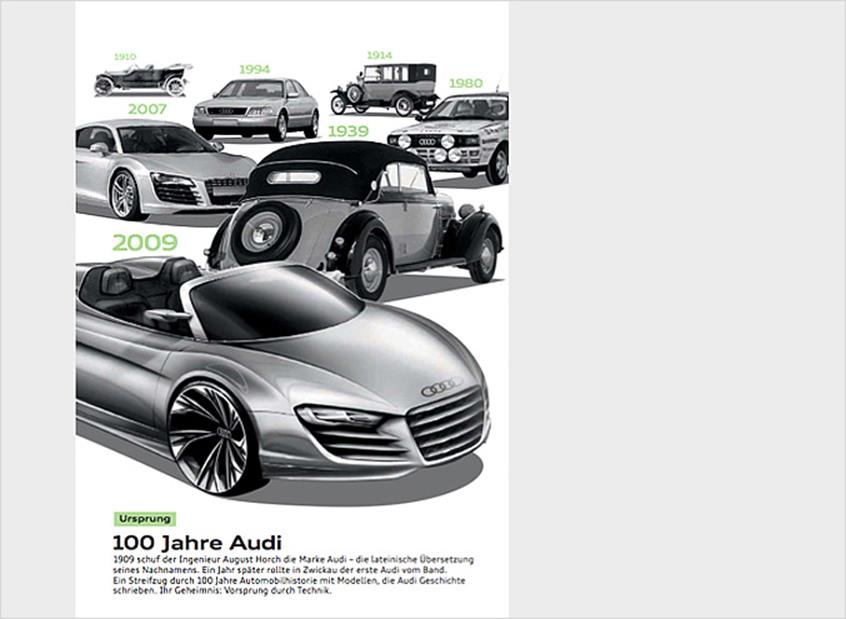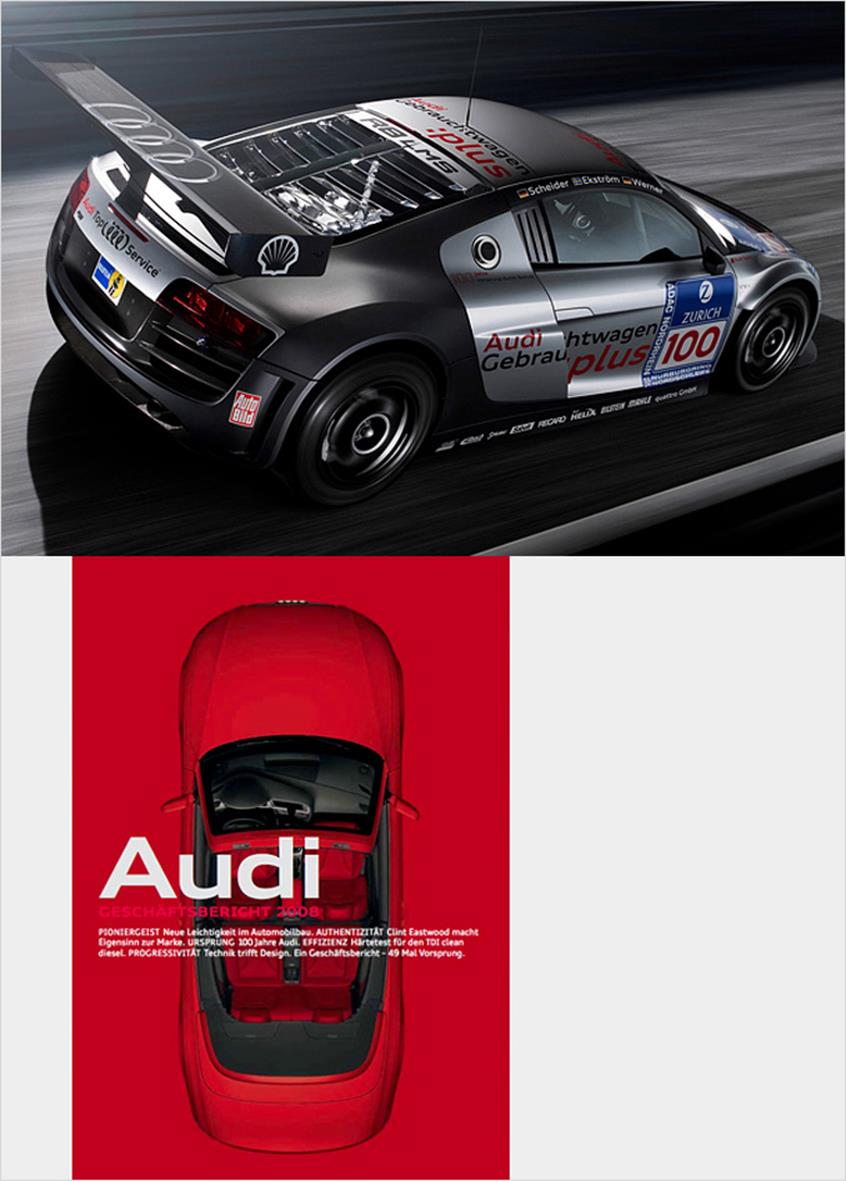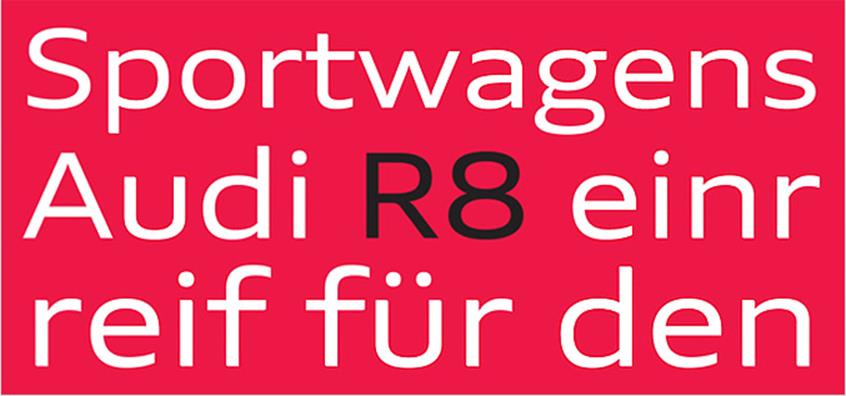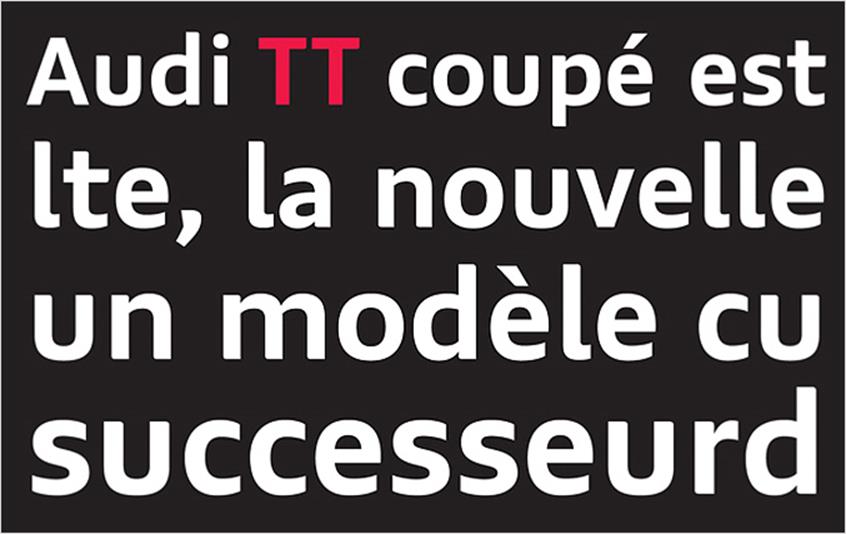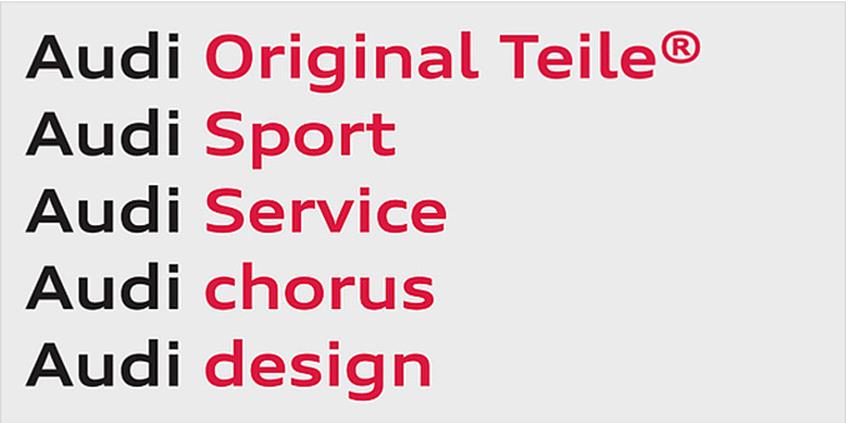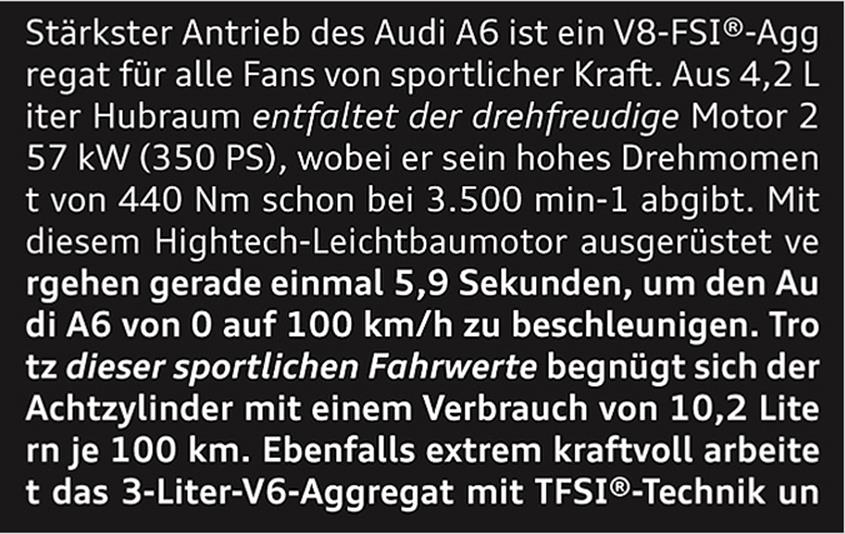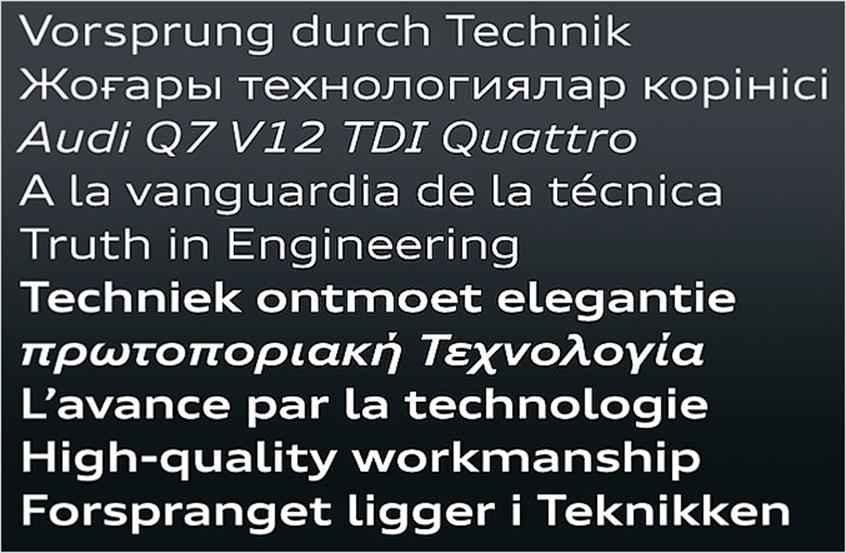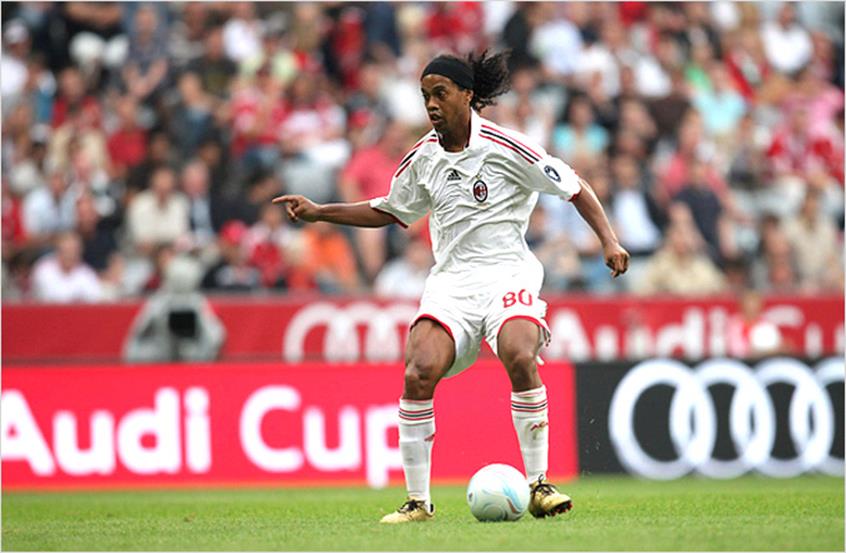
AudiType, Part1_아우디 전용서체의 탄생
2008년 ~ 2009년 사이에 제작된 아우디 전용서체(AudiType)는 출시와 더불어 글로벌 타이포그래피 커뮤니티에 빠르게 전파되어졌다. 이 글에서는 이미 몇 번은 소개되었을 아우디 전용서체의 주요특징 뿐 아니라 메타디자인의 지휘하에 이루어진 디자인 프로세스와 글로벌 브랜드 작업에 포커스를 맞추어 아우티서체를 소개할 것이다. 메타디자인은 아우디 전용서체의 제작을 맡은 베를린의 종합디자인회사이다.
아우디는 이미 잘 알려진 대로 자동차 업계에서 혁신적인 기업으로 꾸준하게 자리매김해온 회사로 고전적 우아함과 기술적 혁신성이 잘 조화된 제품군을 갖추고 있는 독일을 대표하는 브랜드이기도 하다. 독일 잉골슈타트(Ingolstadt)에 자리한 아우디 본사는 설립 100주년을 기념하여 회사 이미지 재고를 위한 여러 프로젝트를 진행시켰고, 그 중 한가지가 기업전용서체의 제작이었다. 디자인 종합회사 메타디자인의 총괄 아래, 아우디 서체의 디자인을 맡게 된 볼드 먼데이(Bold Monday)의 네덜란드 서체디자이너 폴 반 데 라안(Paul van der Laan)은 프로젝트 진행 초기 아우디의 새로운 서체의 필요성을 크게 느끼지 못했다고 한다.
Paul van der Laan
‘나는 자동차 매니아는 아니다. 하지만 아우디의 디자인 감각에는 언제나 경의를 표해왔다. 또한 아우디가 이전에 사용했던 유니버스체를 아주 좋아하는 팬이기도 하다. 아우디의 전용서체 디자인을 위해 그들의 발전과정을 살펴봤을 때, 유니버스체가 아우디의 기술적이고 클래식한 이미지와 매우 조화롭다는 것을 느낄 수 있었다. 그러나 1998년 ‘아우디 TT’를 시작으로 아우디는 보다 스포티(sporty)하고 세련됨을 추구하는 이미지로 변모하기 시작했다는 것을 알 수 있었다.’
▲ 100 Years of Audi taken from the Audi 2008 Annual Report
또한 럭셔리 스포츠카 아우디 R8(Audi R8)이 출시됐을 때, 반 데 라안은 당시 아우디의 상업광고들을 보며 ‘왜 소수의 사람만이 살 수 있는 차를 광고해야 하는가?’라는 의구심을 가지기도 했다. 돌이켜보면 이런 의구심은 반 데 라안으로 하여금 처음의 생각돠는 달리 유니버스가 아닌 아우디만의 새로운 서체가 필요하다는 것에 고개를 기울이게 만들었던 계기가 되었다.
▲ Cover : Audi 2008 Annual Report
아우디 서체 총 지휘를 담당한 메타디자인은 오랜 시간 컴페티션을 진행했고, 최종적으로 선택된 것이 반 데 라안, 반 로즈말렌 듀오의 볼드 먼데이였다. 메타디자인이 진행한 컴페티션은 상당히 독특한 방식으로 이뤄졌는데, 몇몇의 유망한 디자이너들에게 일정한 비용과 기간(두 달)을 주고 산세리프(Sans serif)체의 노멀(Normal), 볼드(Bold), 익스텐디드 노멀(Extended Normal), 익스텐디드 볼드(Extended Bold) 등 4가지 스타일로 새로운 문자집합을 디자인하도록 요구한 것이다. 이를 위해 각 디자이너들에게는 디자인에 필요한 무드 보드, 각종 그래프와 다이어그램, 마케팅 단어가 제공되었고, 볼드 먼데이는 제공된 것 이상의 마케팅 단어들을 사용한 서체 견본집으로 아우디 서체 프로젝트를 거머쥘 수 있었다.
▲ AudiType Extended : First Proposal
▲ AudiType Normal : First Proposal
반 데 라안에 따르면 컴페티션의 결과가 나온 뒤, 한동안은 진행이 더디었다고 한다. 그 이유는 디자이너 측과 아우디의 대표들 간의 의견차 때문이었는데, 볼드 먼데이의 두 디자이너들은 인쇄상에서 나타나는 서체의 미세한 측면들까지 고려하는 반면 아우디의 대표들은 단순히 그들의 로고와 로고로 만들어지는 파생물에 어울리는 지에만 집중했다고 한다.
Van der Laan
‘우리는 서체가 긴 단락으로 조합되었을 때, 아름다움이 느껴지도록 제안했다. 그리고 그 제안을 통과시키도록 많은 노력을 기울였지만, 아우디의 대표들은 오로지 그들의 회사를 표현하는 철자 4개의 타이포그래피만을 보고 있었다.’
결국 볼드 먼데이는 두 번째 제안을 해야 했다. 이번에는 보다 폭이 넓은 스타일에 주안점을 두고 작업한 디자인을 선보였다.
▲ AudiType : Second Proposal
Van der Laan
‘처음 제안에서는 미세하게 인본주의적인 콘트라스트를 가미하였는데, 폭이 넓은 비율의 글자들에서는 그 특징이 드러나는 것이 거의 불가능 했다. 가능했더라도 억지스럽거나 우스꽝스러운 느낌이 나는 것을 피하기는 어려웠을 것이다. 결국 첫 번째 제안을 뒤로하고, 많은 디테일들을 보강하여 새로운 프리젠테이션을 만들었고, 그것으로 프로젝트를 따낼 수 있었다. 2008년 8월 우리와 아우디의 마케팅 디렉터는 메타디자인에서 공식적으로 프로젝트 계약을 체결했다.’
비교적 긴장된 제안과정이 지난 후, 볼드 먼데이는 메타디자인의 크리에이티브 팀과 함께 자유로운 분위기 속에서 남은 진행상황에 대해 의견을 나누었다. 메타디자인은 여기서 새로운 서체는 산세리프체로 두 가지 너비와 무게, 그리고 전부 로만체와 이탤릭체로 제작될 것 등 기본적인 아이디어를 전달했다. 이어 이어진 컨셉에 대한 대화에서는 서체의 ‘남성성’과 ‘평면성’이 거론되었다.
▲ AudiType : Finished regular width
그리스문자나 키릴문자가 추가되는 부분에서는 이 문자들이 가진 미묘한 뉘앙스 차이에 관련하여 많은 문제들이 제기되었다. 이에 기본 라틴 알파벳 문자와 서로 호응될 수 있는 디자인 컨셉이 필요했고, 볼드 먼데이는 반 데 라안의 예전 제자이자 러시아에서 타입디자이너로 활동 중인 일야 루더만(Ilya Ruderman)의 도움을 받았다. 루더만은 네이티브 러시아 타입디자이너의 관점으로 피드백을 제공했다.
▲ AudiType Cyrillic and Greek shown with the standard Latin setting.
중국어, 일본어, 그리고 한국어 문자들을 지원하는 수많은 글리프들이 포함된 세트를 확장하는 것은 더욱 중요하게 고려됐다. 이는 아시아 문화 속 아우디 브랜드를 확고히 하기 위해 결정된 사항이다. 아시아 언어의 폰트들은 너비가 추가되거나 확장된 글꼴 스타일이 여전히 부족한 상황이어서 라틴 문자의 서체 패밀리와는 다른 방식이 요구되었다.
2009년 여름 그들의 100주년 기념과 함께 아우디의 새로운 서체가 런칭된 후, 때마침 뮌헨에서는 바르셀로나, 멘체스터 유나이티드, 보카 주니어스, 바이에른 뮌헨 등이 참여한 프레스티지 풋볼 토너먼트 ‘아우디 컵’이 개최되었다. 이 행사는 짧은 시간 내에 아우디 서체를 전파시키는 계기가 되었다. 축구장 내의 광고, 배너, 셔츠와 스크린 등 곳곳에서 아우디의 새로운 서체를 접할 수 있었기 때문이다. 이후 아우디 서체는 종종 뜻하지 않게, 혹은 놀라운 방식들로 우리 앞에 선보여지고 있다.